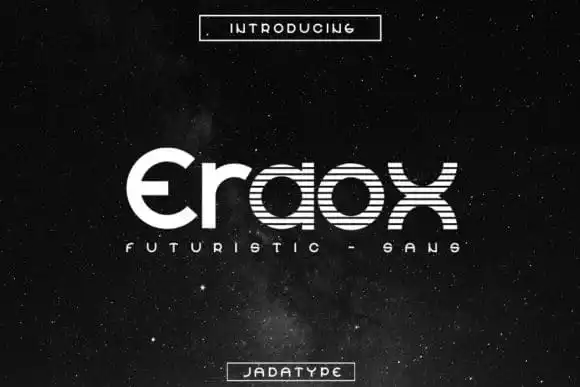
Eraox Display Font – Fonte Grátis
Eraox Display Font
A Eraox Display Font apresenta uma aposta moderna no tema futurista-sci-fi. Esta tipografia é simples, aguda e oferece muitas alternativas que podem ser acessadas facilmente tanto com letras maiúsculas quanto minúsculas. Ela traz um estilo único e atual que a torna perfeita para aplicativos como flyers, jogos, cartazes e muito mais. Composta pelo designer 99designs, esta fonte oferece uma experiência visual dinâmica e moderna que complementará qualquer projeto gráfico com precisão e elegância. Não hesite em explorar a Eraox Display Font para adicionar um toque especial a seu próximo design.